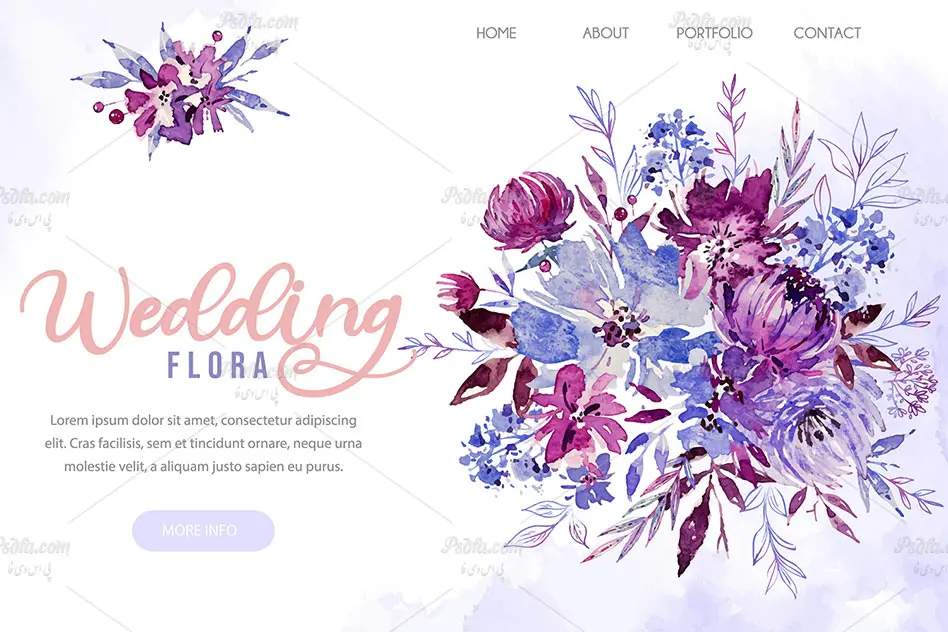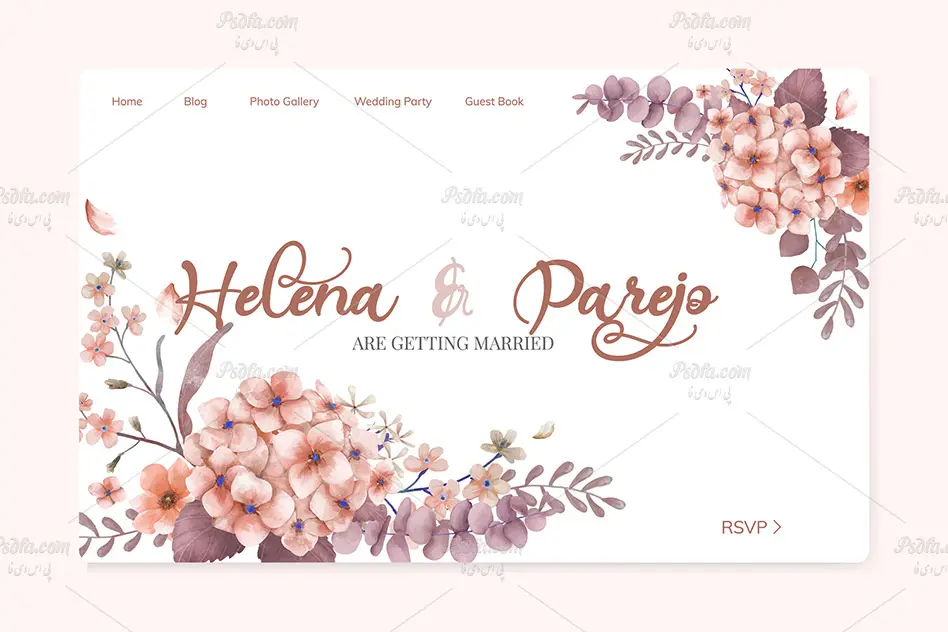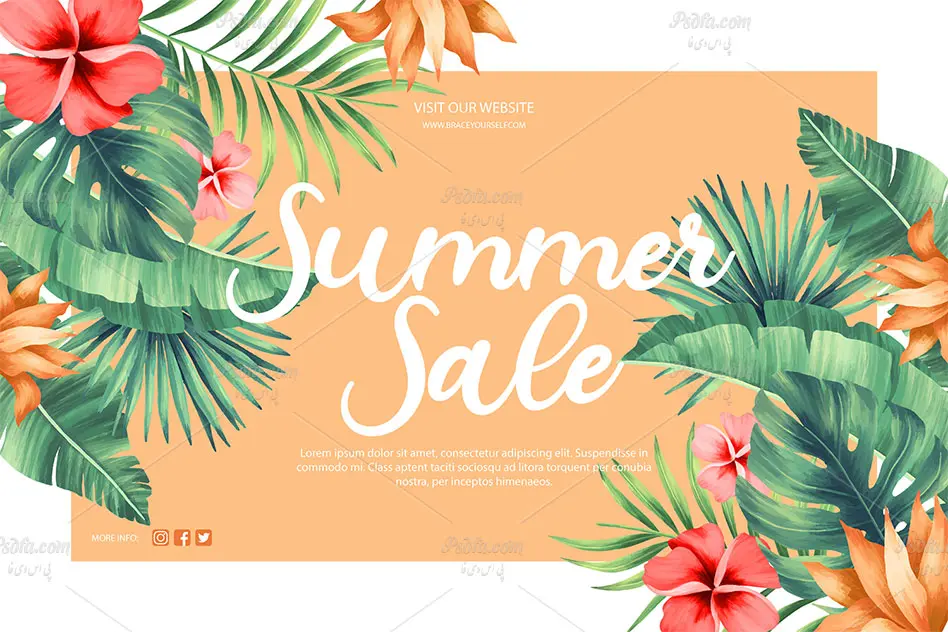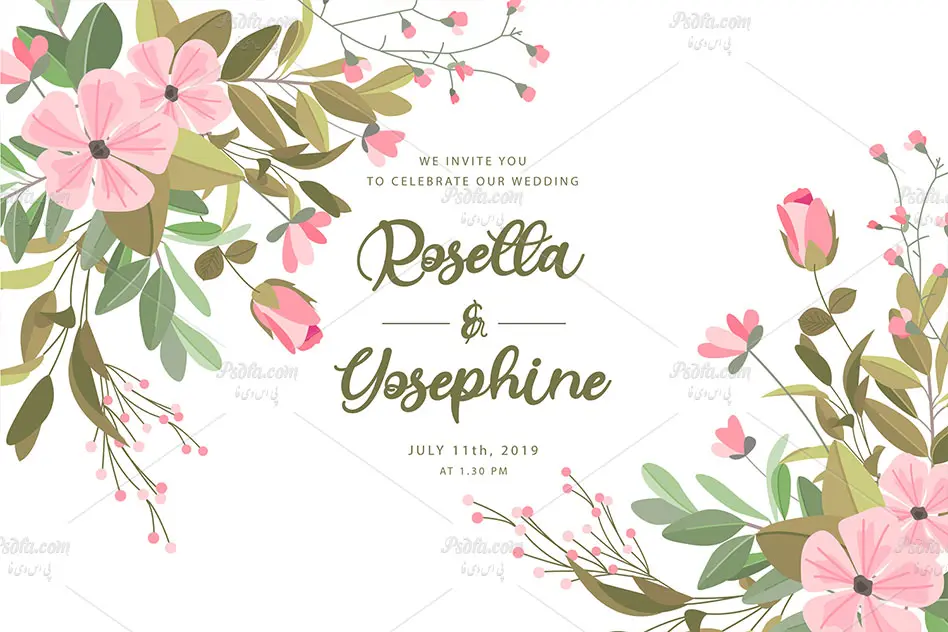
فونت برای طراحی کارت تبریک ، کارت عروسی و … Helegra
فونت برای طراحی کارت
در این مطلب شاهد فونت Helegra مناسب برای طراحی انواع کارت تبریک ، کارت پستال ، کارت عروسی و … می باشید. این فونت فوق العاده زیبا در قالب 2 فایل ttf و otf بر روی سایت قرار گرفته است که با نصب یکی از این دو فایل در پوشه فونت های سیستم قادر به استفاده از آن در تمام نرم افزار های گرافیکی و ویرایشگر متن از جمله نرم افزار فتوشاپ ، افترافکت ، ایلاستریتور ، مجموعه نرم افزار آفیس (ورد ، پاورپوینت) و … خواهید بود. فونت Helegra در وزن معمولی (Regular) طراحی شده است که می توان از آن در طراحی کارت ویزیت ، کارت تبریک ، کارت عروسی ، بروشور ، پوستر ، انواع بنر و … استفاده نمود.